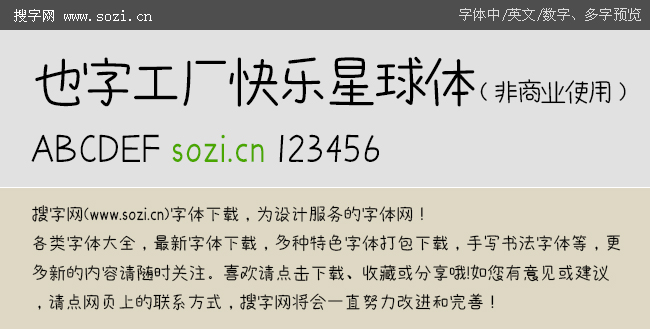
也字工廠快樂(lè)星球體
搜字網(wǎng)給大家提供一款也字工廠快樂(lè)星球體(非商業(yè)使用)中文字體下載,也字工廠快樂(lè)星球體是一款卡通字體,字體是可愛的書寫風(fēng)格,非常可愛有趣,具有很好的視覺效果。適合應(yīng)用于兒童繪本、兒童海報(bào)、網(wǎng)頁(yè)設(shè)計(jì)等應(yīng)用(此字體為個(gè)人非商用版,商用可以聯(lián)系:官方網(wǎng)址:https://yefont.com/home,聯(lián)系方式:13798980448)。